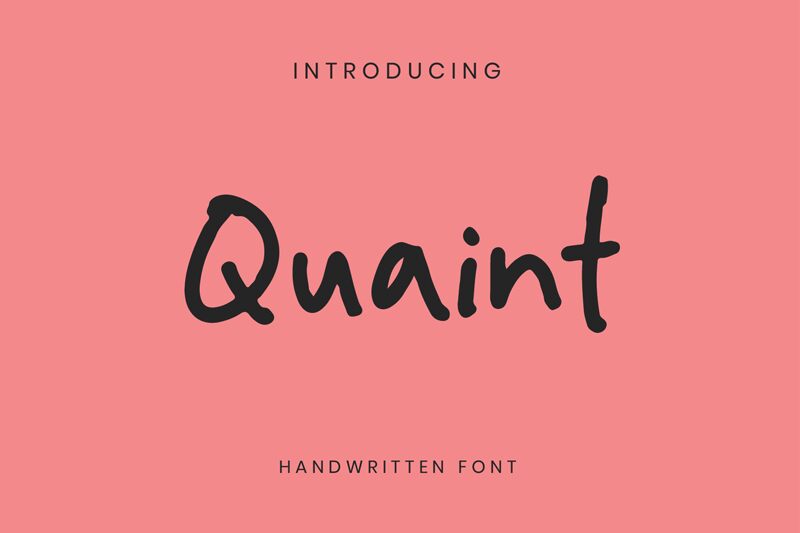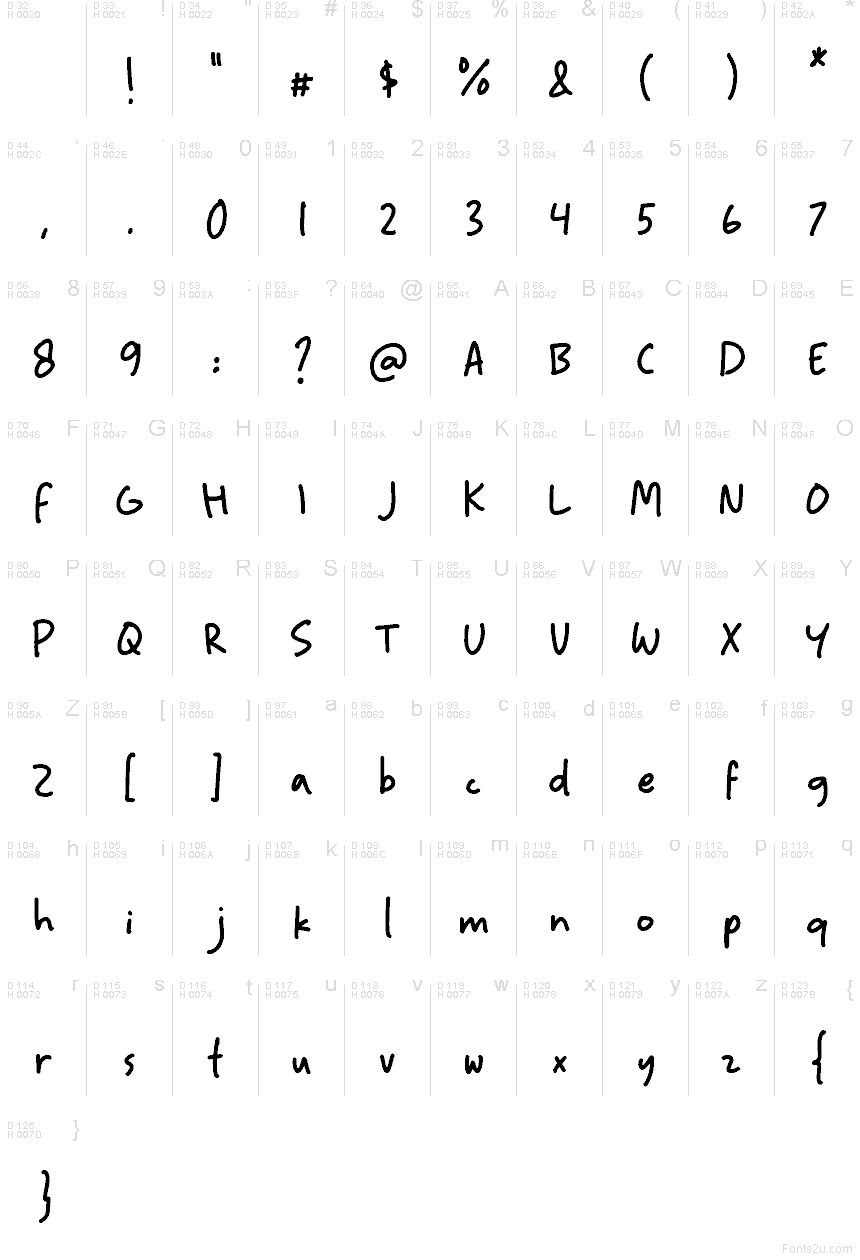
Quaint HF par Agung Rohmat est une police manuscrite décontractée et gratuite, au rythme souple et amical. Les lettres semblent avoir été tracées d'un geste rapide, avec des courbes arrondies, un tracé légèrement irrégulier et une spontanéité informelle qui privilégie la chaleur à la perfection géométrique.
Elle s'intègre naturellement dans l'identité visuelle de cafés, le packaging, les cartes de vœux, les réseaux sociaux et les titres courts, là où une touche humaine est préférable au formalisme. En tant que police gratuite, elle fonctionne également très bien pour des titres ou des logos simples, surtout lorsque vous recherchez un lettrage personnel et légèrement ludique, sans pour autant tomber dans le style script traditionnel.